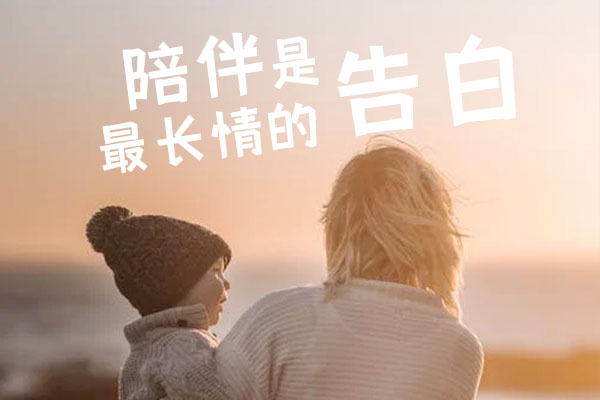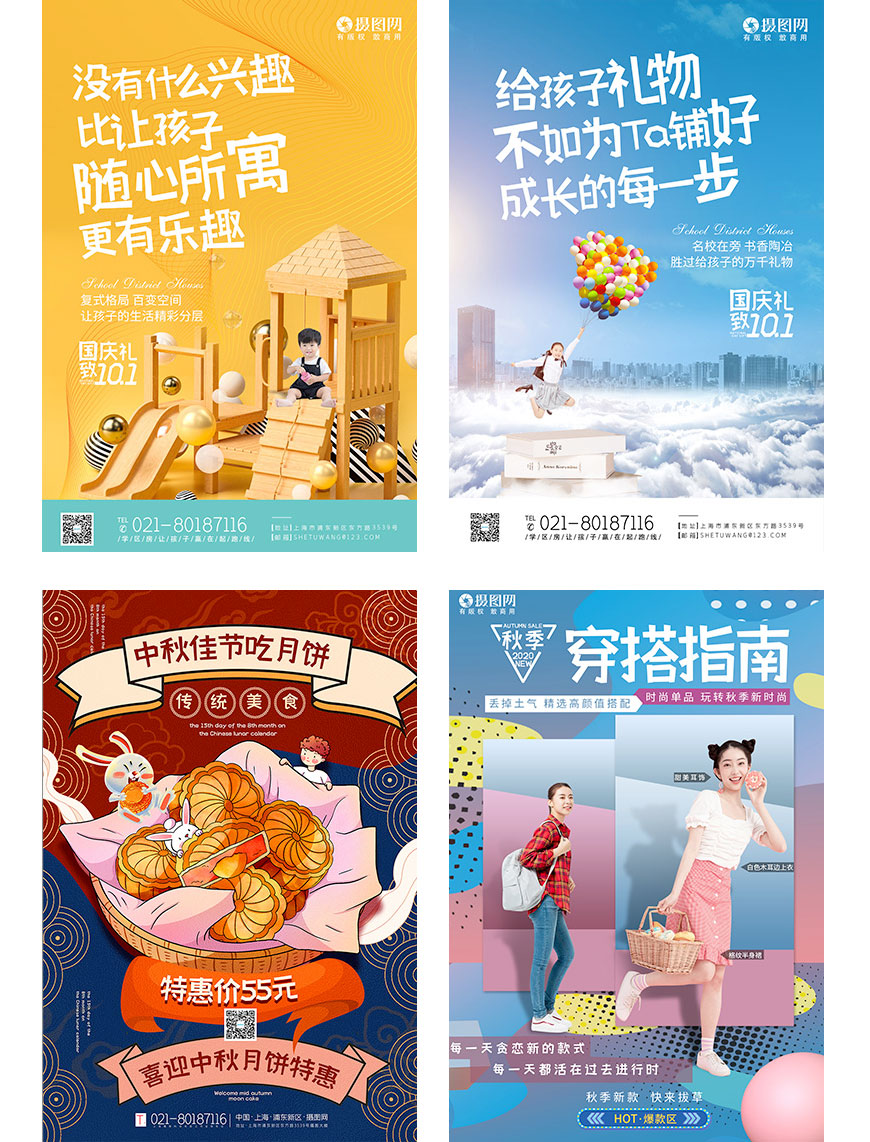
摄图摩登小方体
摄图摩登小方体:未来感十足的创意黑体字
摄图摩登小方体遵循GB2312编码标准,共包含6995个字符。其中,6763个简体汉字、52个大小写字母、10个数字以及170个标点符号,无论是用于电商、广告、还是美食等商业宣传和包装设计,都能展现出其出色的表现力。
这款字体的设计灵感源于对未来空间的想象,传达出一种未来与现实的交融感。笔画方正质朴而又不失灵气活力,适中的字体笔画粗度和几何感的细节设计,让字体在视觉上具有出色的应用表现。独特的负形空间处理技术使字体整体稳重端庄而不失活泼,增加了趣味性。
摄图摩登小方体的出现,不仅解决了设计师在寻找适合未来主题的字体时遇到的困难,也为企业提供了新的、免费的字体选择。设计师们现在可以利用这款字体轻松打造出既新颖又符合品牌形象的设计作品。无论是用于商业宣传、包装设计还是社交网络的个性化用字,摄图摩登小方体都将是理想的选择。作为一款汇集了中西方字形特点的创意黑体字摄图摩登小方体无疑将成为未来设计的新趋势。
摄图摩登小方体效果预览
摄图摩登小方体字体效果预览